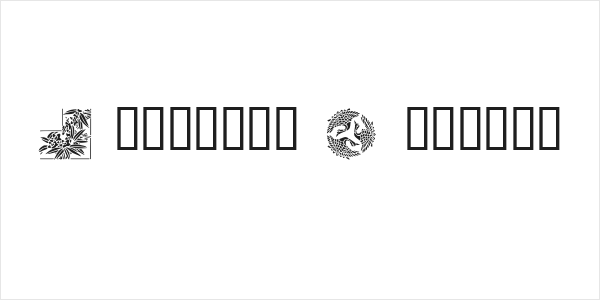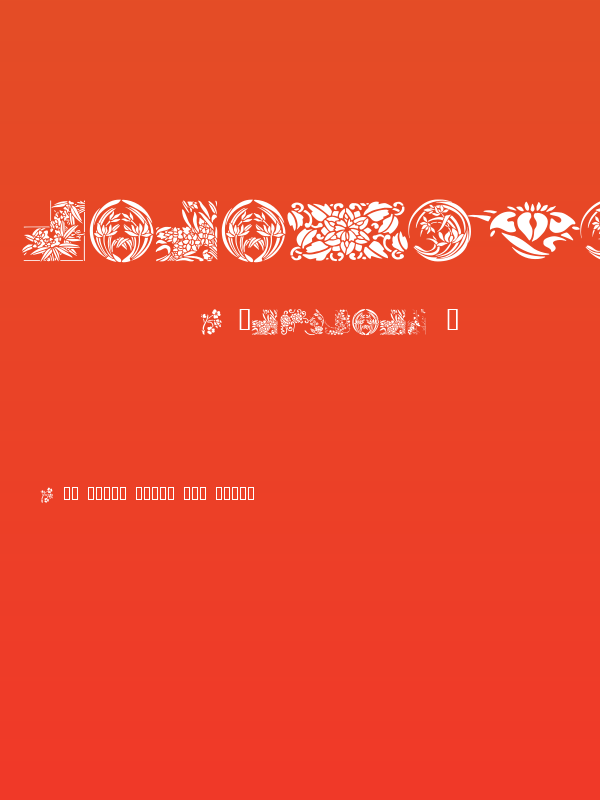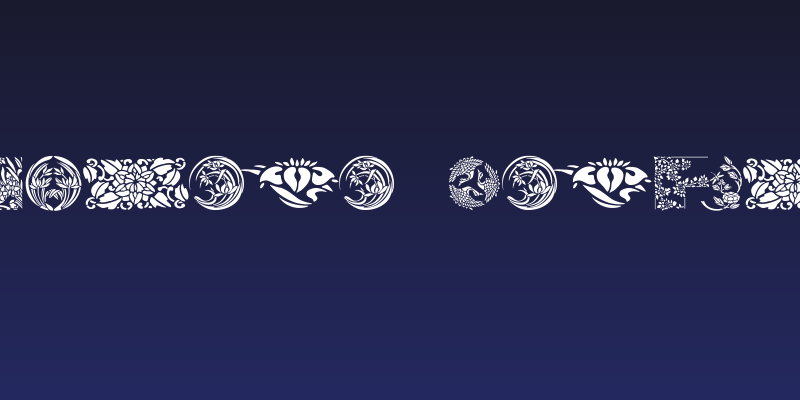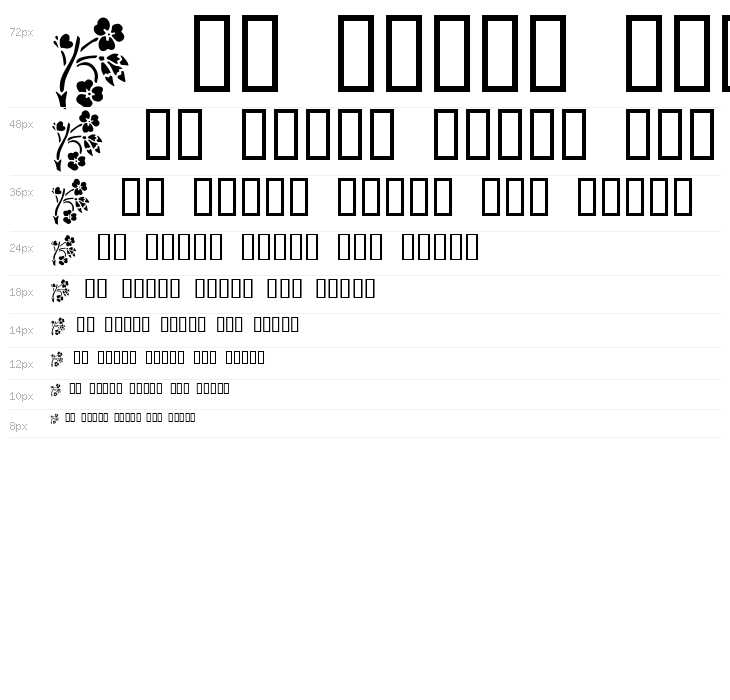
Japanese Designs Font
✎ Dingbats
| Vorgeschlagene Projekte | Ideal for cultural event posters, themed invitations, artistic branding, and decorative signage. |